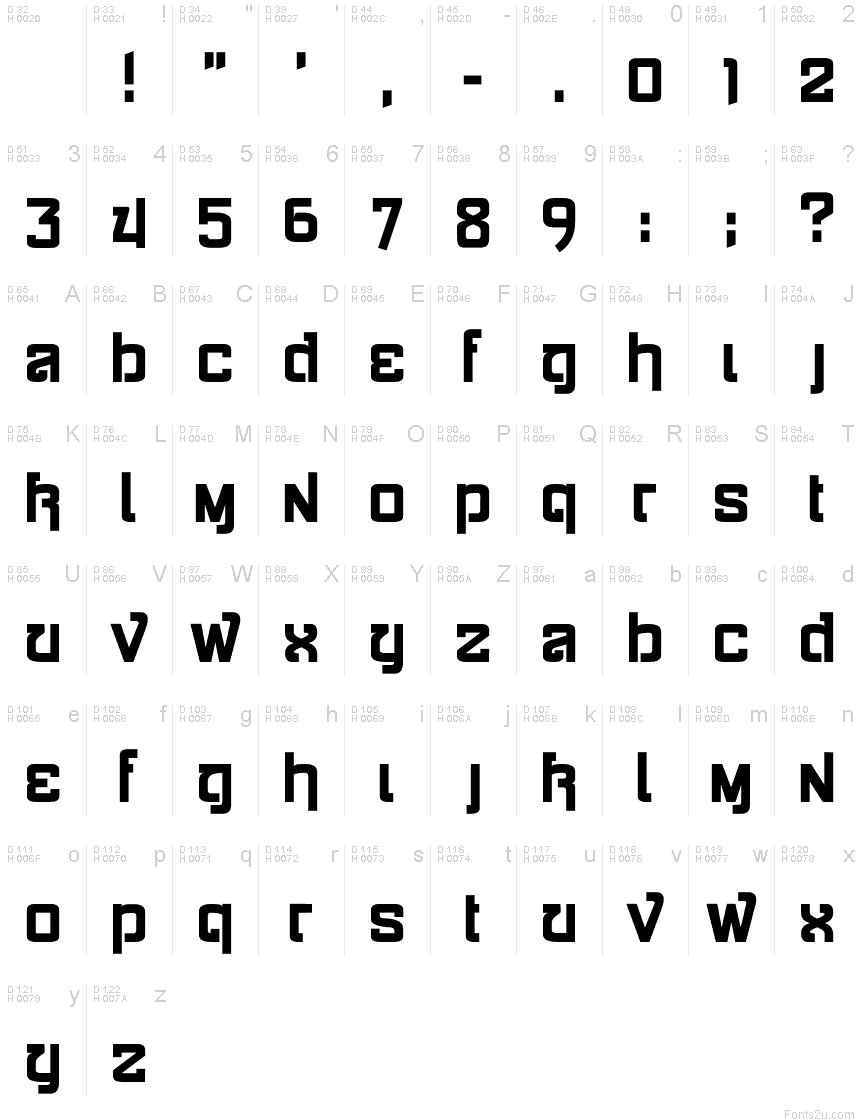
Siamese Katsong di Vic Fieger (Xaviera Comics) è un font display gratuito in stile thailandese, caratterizzato da un ritmo solido e squadrato con un’impronta decisamente da poster. Le lettere sembrano scolpite in forme nere e spesse, con angoli arrotondati, spazi interni stretti e un mix giocoso di struttura latina e curve d’ispirazione thailandese che conferisce all’alfabeto un ritmo compatto e massiccio.
È una scelta naturale per il branding di ristoranti, poster di viaggio, copertine di fumetti, flyer per club e packaging, dove il lettering stesso determina l’atmosfera. Essendo un font gratuito, dà il meglio di sé in brevi impaginazioni display – titoli, intestazioni e wordmark in stile logo – grazie alle sue forme dense e alle curvature stilizzate che creano subito una forte silhouette grafica.